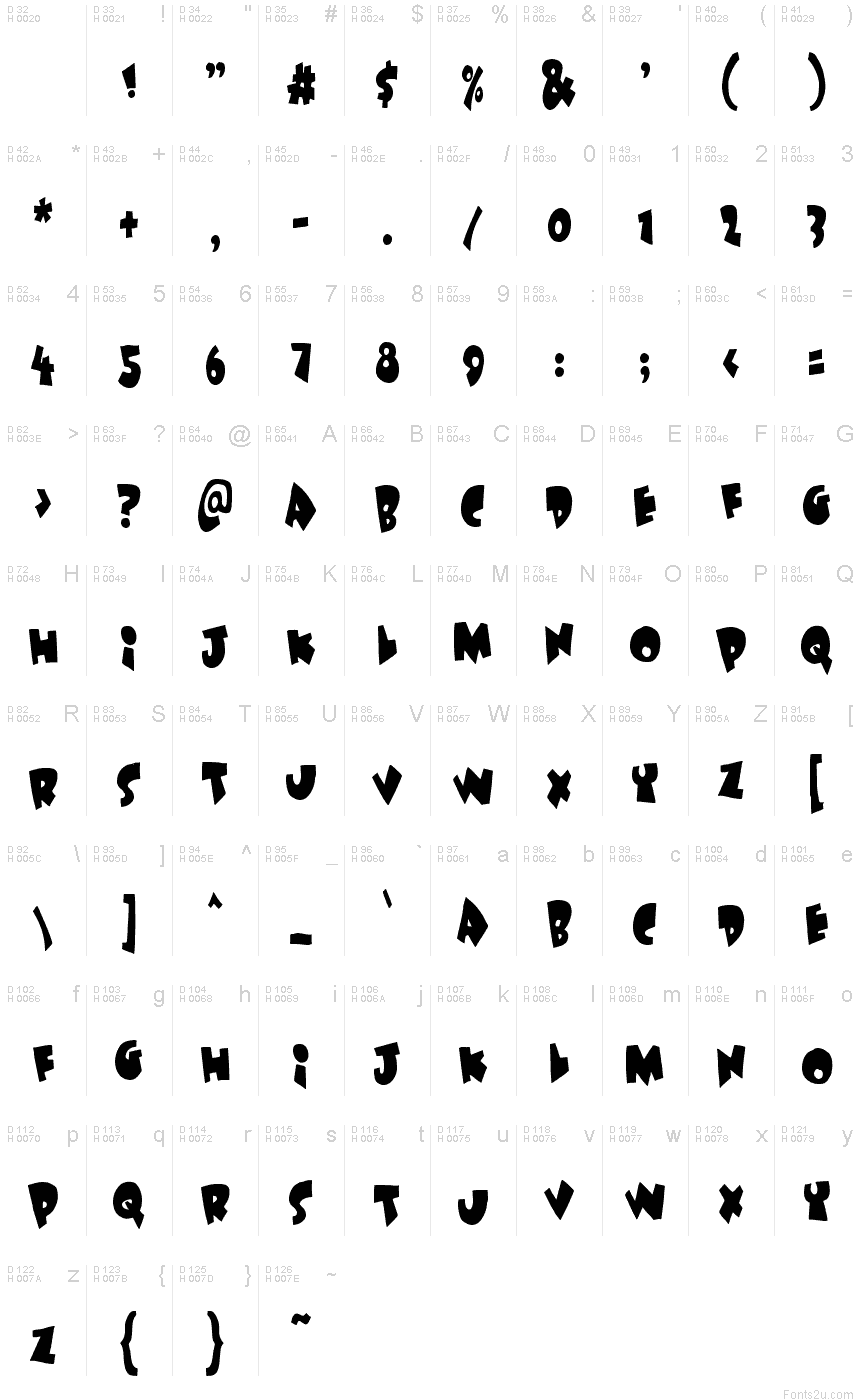
Under attack
Under Attack by Jakob Fischer je bezplatné titulkové písmo v duchu cartoon-horror, jehož písmena vypadají, jako by byla narychlo vystřižena z papíru a nalepena na místo. Velká písmena se naklánějí, vyčnívají a kymácejí, mají masivní siluety a ostré hrany – díky tomu působí písmo jako divoký komiksový chaos, nikoliv jako úhledný a uspořádaný řádek.
Tato syrová energie se skvěle hodí na nadpisy plakátů, halloweenské letáky, titulky her, obálky zinů a výrazné obaly, kde má bezplatné písmo na první pohled působit nespoutaně. Dobře poslouží také pro krátké názvy kapel, úvody kapitol a jiná krátká textová místa, protože písmena jsou dostatečně tučná, aby unesla vtip, a dostatečně křivá na to, aby udržela napětí.